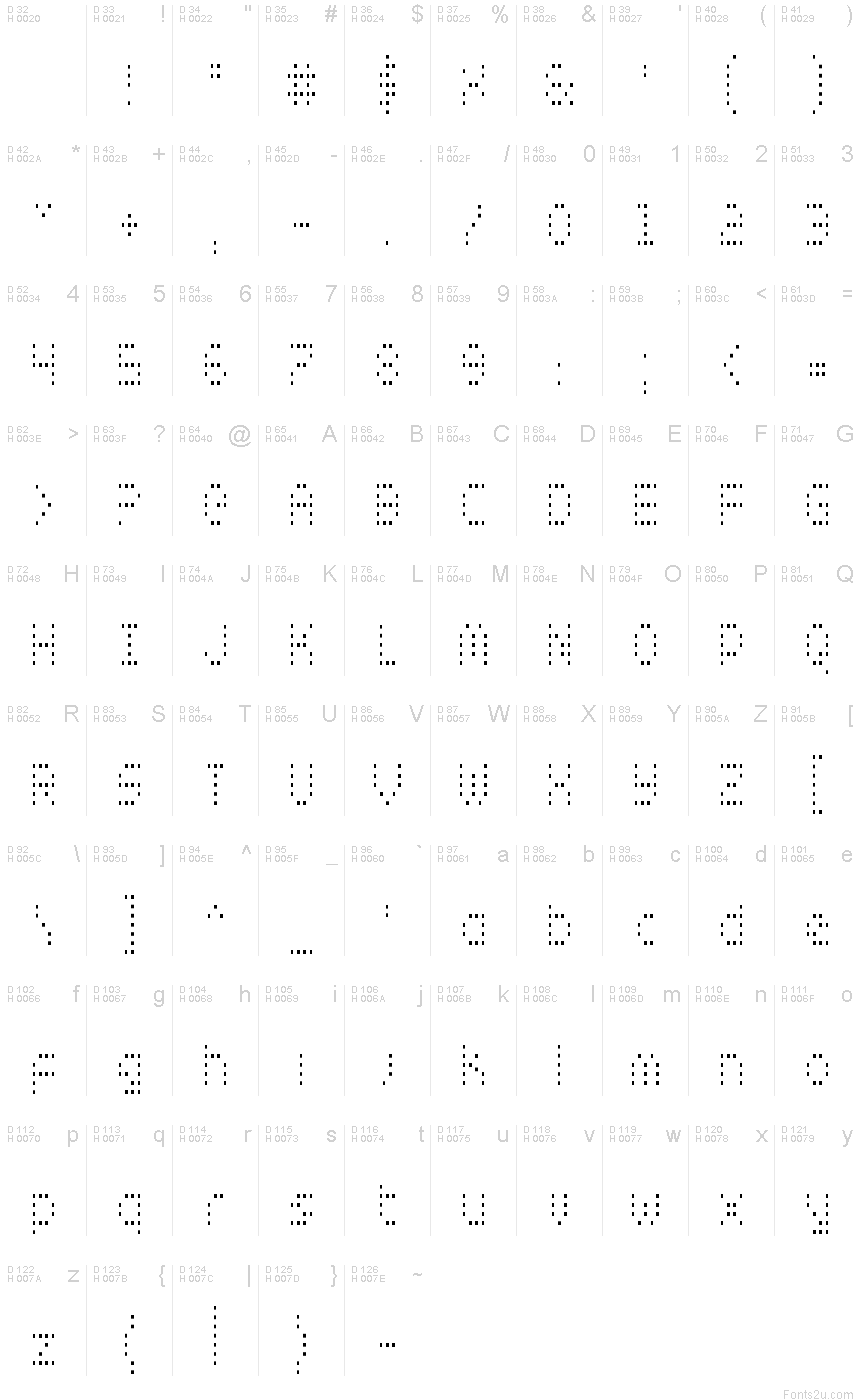
Zado Condensed od Iconian Fonts to darmowy cyfrowy font typu display, zbudowany z wyraźnych, kwadratowych pikseli. Litery wyglądają jak zredukowane do siatki punktów i krótkich kresek, co nadaje krojowi surowy, arcade-techowy klimat, przypominający bardziej sygnał lub odczyt z ekranu niż zwykłe pismo.
Dzięki temu idealnie pasuje do grafik w grach, plakatów sci-fi, makiet interfejsów, ulotek o programowaniu czy kompaktowych nagłówków, gdzie poszukiwany jest darmowy font o wyrazistym, bitmapowym charakterze. Sprawdza się także w krótkich tekstach i nagłówkach w stylu etykiet, ponieważ rytm powtarzających się bloków sprawia, że nawet krótkie słowa wyglądają intencjonalnie, jak wygenerowane przez maszynę.
Zado Condensed